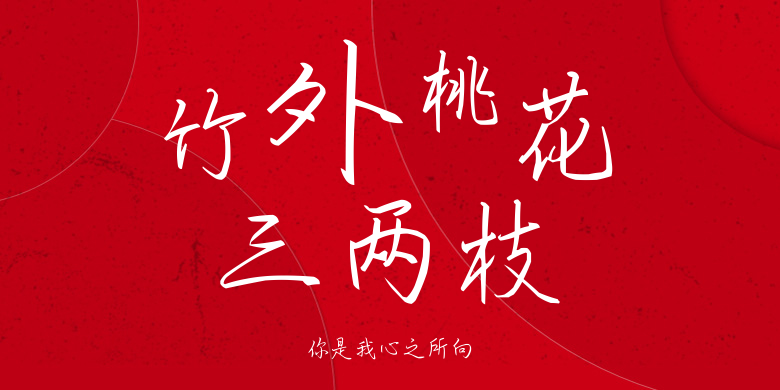
你是我心之所向
你是我心之所向,这款字体结构工整、笔画清晰,兼顾美观与易读性,适用于标题、正文、海报、包装、LOGO 等多种场景。字形优雅稳定,风格百搭耐看,适配日常排版与创意设计,让文字呈现更舒适、更具质感。你是我心之所向一笔一画,皆是细节,以均衡的比例、流畅的线条打造舒适视觉体验,字形端正大气,风格简约现代。无论是商业设计、品牌宣传还是日常排版,都能轻松驾驭,让文字更有格调与力量。你是我心之所向字体下载。